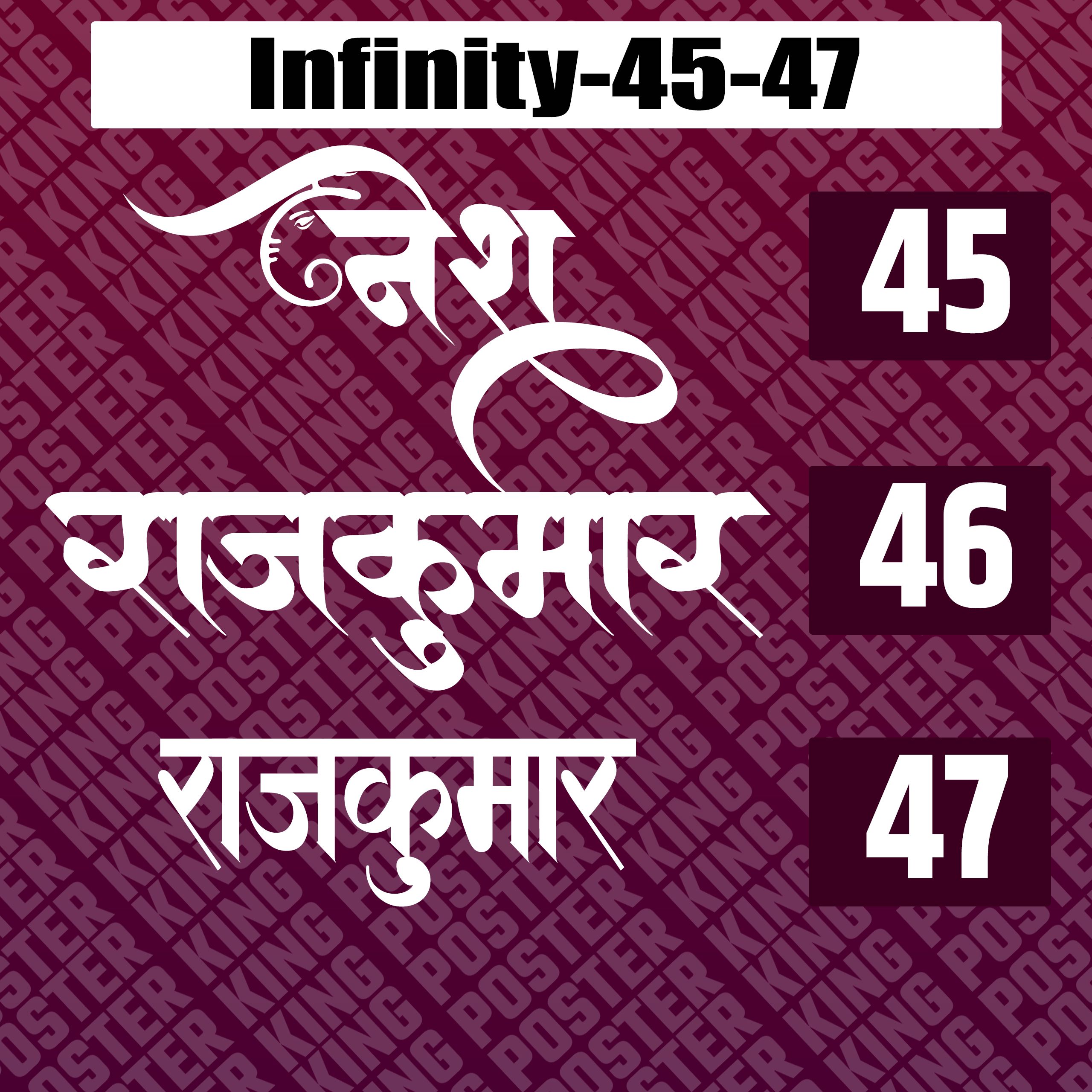
यह फॉन्ट पैक विशेष रूप से उन ग्राफिक डिज़ाइनों के लिए तैयार किया गया है जहाँ स्टाइलिश हिंदी टाइपोग्राफी और कैलीग्राफी की आवश्यकता होती है। इस बंडल में Infinity सीरीज के तीन सबसे लोकप्रिय फॉन्ट—45, 46 और 47 शामिल हैं, जो आपके डिज़ाइन को एक पेशेवर और कलात्मक लुक प्रदान करते हैं।
फॉन्ट की मुख्य विशेषताएँ:
• यूनिक आर्टिस्टिक स्टाइल: शब्दों को लिखने के लिए बेहतरीन स्टाइल दिए गए हैं।
• बहुमुखी उपयोग: ये फॉन्ट्स विजिटिंग कार्ड, शादी के कार्ड (Wedding Cards), फ्लेक्स बैनर, और सोशल मीडिया पोस्ट के लिए एकदम सटीक हैं।
• ट्रेंडिंग डिज़ाइन: वर्तमान में ये कैलीग्राफी फॉन्ट्स ग्राफिक डिजाइनिंग की दुनिया में सबसे अधिक डिमांड में हैं।
यह बंडल उन डिजाइनरों के लिए एक अनिवार्य एसेट है जो साधारण टेक्स्ट को भी एक प्रीमियम मास्टरपीस में बदलना चाहते हैं।
• Pillar of Calligraphy: हिंदी कैलीग्राफी के तीन शानदार वेरिएंट्स (Infinity 45, 46, 47) का समावेश।
• Professional Look: आपके विज्ञापनों और निमंत्रण पत्रों को एक राजसी और पारंपरिक लुक देता है।
• High Quality: हर फॉन्ट को बहुत बारीकी से डिज़ाइन किया गया है ताकि बड़े आकार में प्रिंट होने पर भी स्पष्टता बनी रहे।
• Perfect for Names: शादी के कार्ड में दूल्हा-दुल्हन के नाम लिखने के लिए सबसे लोकप्रिय विकल्प।
• Trending in 2026: आधुनिक ग्राफिक डिज़ाइनिंग की नवीनतम माँगों के अनुसार तैयार।